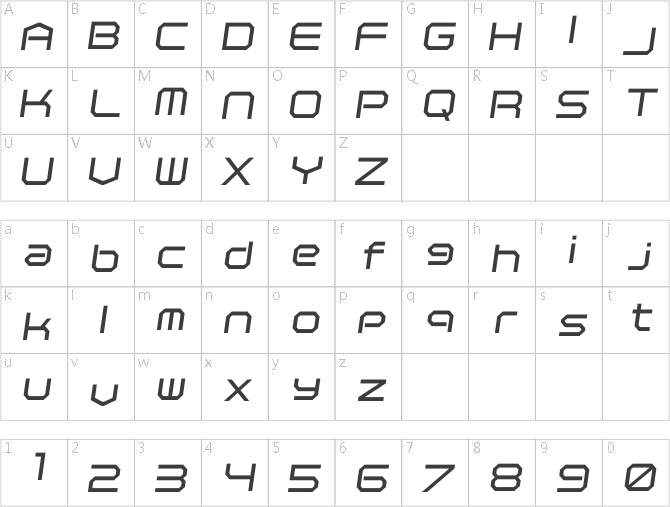
Polentical_Neon_Italic
Polentical_Neon_Italic介紹
Polentical_Neon_Italic字體字庫是一款讓人賞心悅目、百看不厭的英文字體,適合各類廣告和產品包裝設計應用,字體大小0.02MB,格式為ttf字體,上傳用戶是哼哼哈兮,作者/版權方為未知